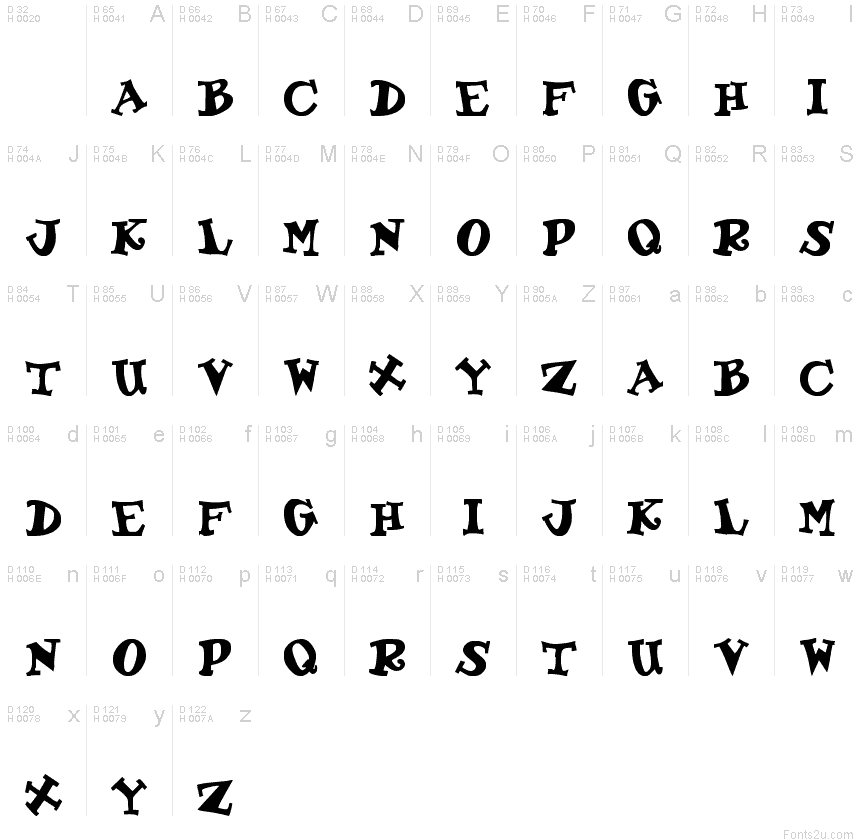
Gadzoox Bold to darmowy, komiksowy krój pisma typu display z masywnymi, „atramentowymi” literami, które drgają w sam raz, by sprawiać wrażenie żywych i ręcznie rysowanych. Każdy znak lekko się wygina i przechyla, nadając nagłówkom pełną energii, kreskówkową dynamikę, nie tracąc przy tym na czytelności. Ciężkie, czarne kształty i zwarty rytm sprawiają, że słowa wyglądają, jakby zostały odbite na stronie grubym markerem.
Gadzoox Bold pozwala natychmiast dodać zabawnego charakteru okładkom książek dla dzieci, kadrom komiksowym, zaproszeniom na imprezy, plakatom arcade, opakowaniom zabawek czy wesołym grafikom do mediów społecznościowych. Ten darmowy font najlepiej prezentuje się w większych rozmiarach, gdzie jego nietuzinkowe krzywizny i nierówny charakter naprawdę mogą błysnąć. Zestaw Gadzoox Bold z prostym bezszeryfowym krojem geometrycznym w tekście głównym i pozwól rodzinie Gadzoox zająć się Twoimi wyrazistymi, radosnymi nagłówkami.
Gadzoox